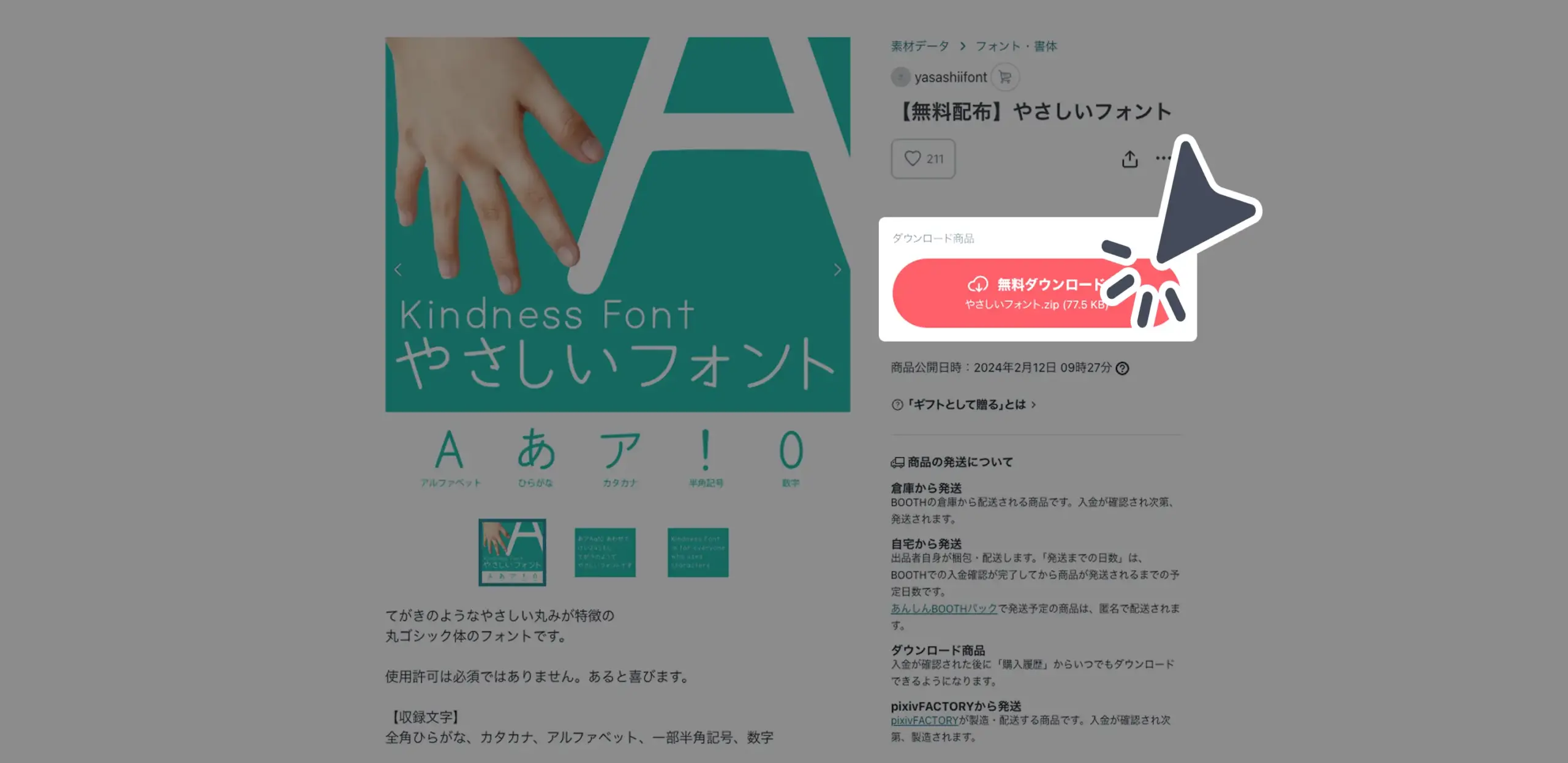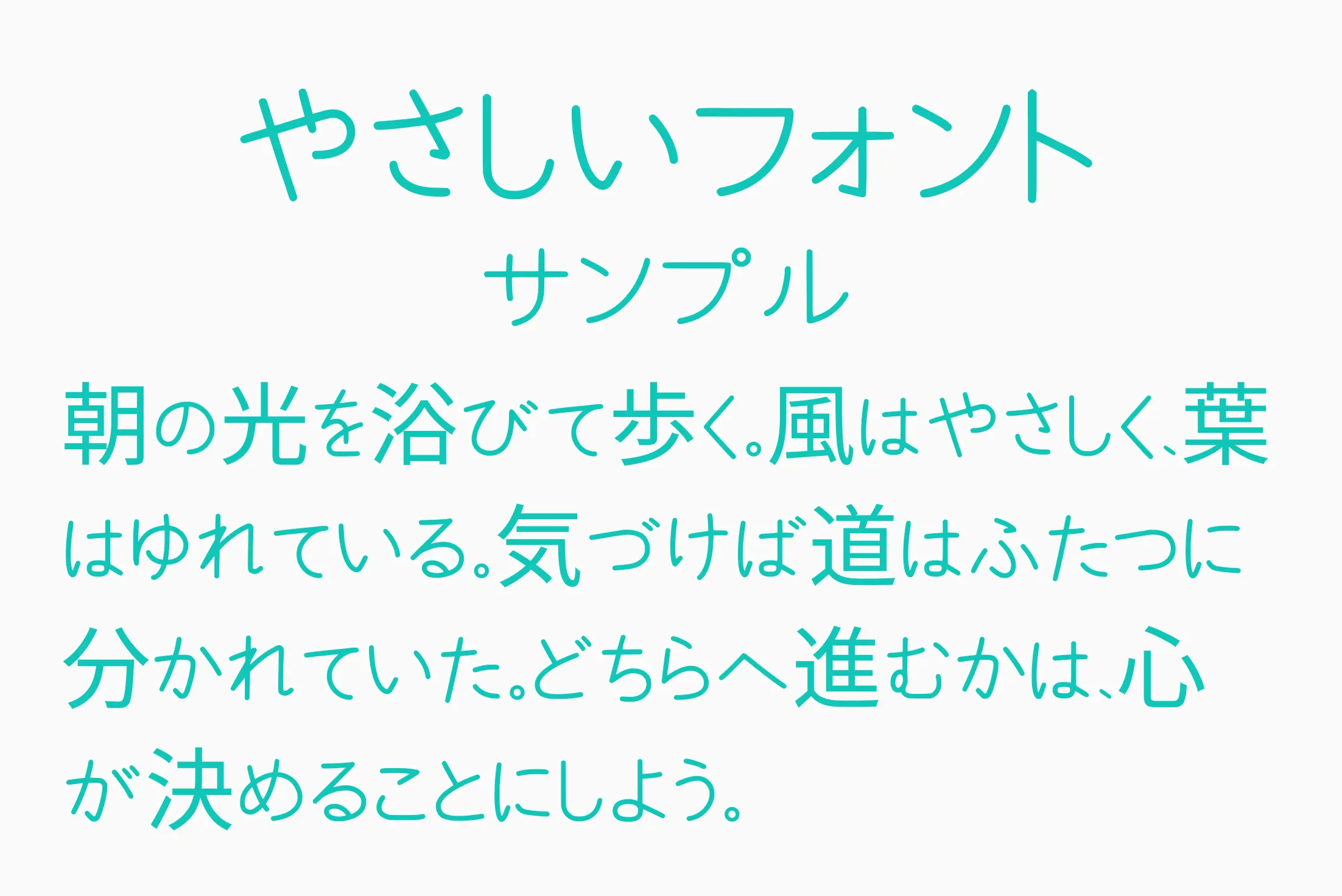
手書き風のやわらかなラインと、読みやすさを両立したナチュラル系フォント。丸みを帯びた文字が親しみやすく、人に寄り添う印象を与えたい場面に最適です。プレゼン資料やPOP、教育・福祉系の配布物、YouTube・SNS投稿、自己紹介スライドなど、「きっちりしすぎず、でもきれいに伝えたい」用途で大活躍します。
やさしいフォント
手書き風のやわらかなラインと、読みやすさを両立したナチュラル系フォント。丸みを帯びた文字が親しみやすく、人に寄り添う印象を与えたい場面に最適です。プレゼン資料やPOP、教育・福祉系の配布物、YouTube・SNS投稿、自己紹介スライドなど、「きっちりしすぎず、でもきれいに伝えたい」用途で大活躍します。